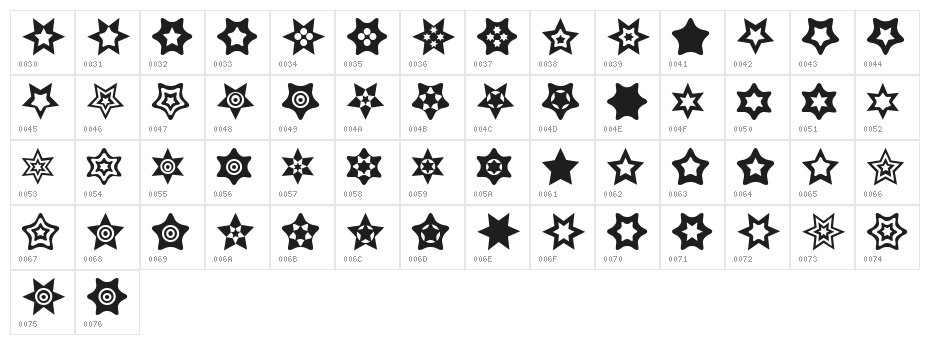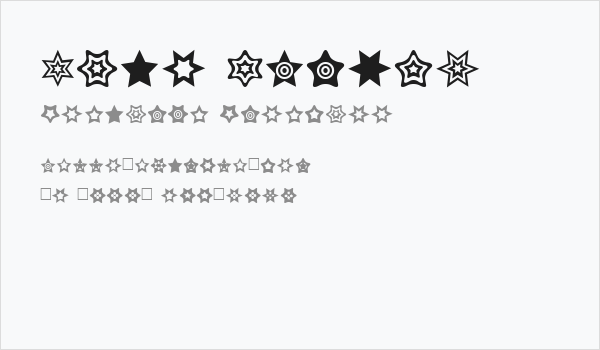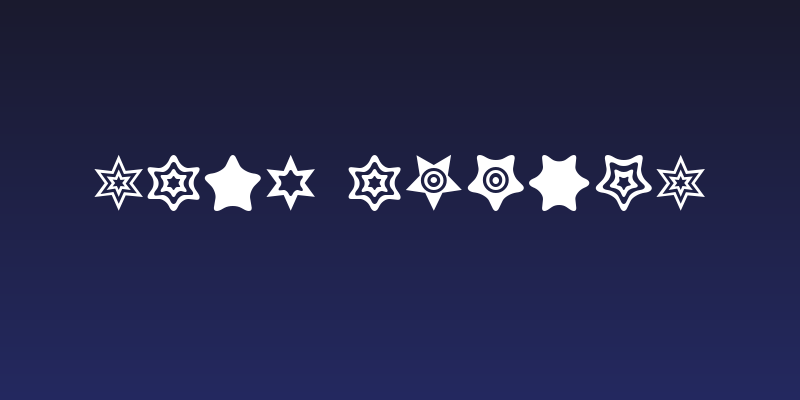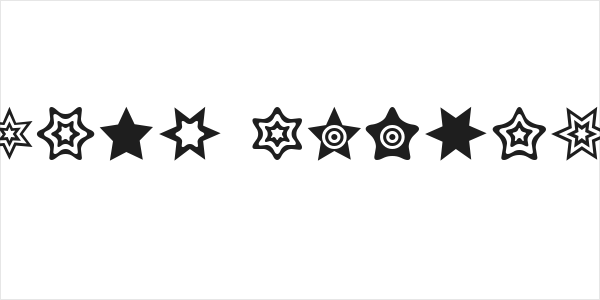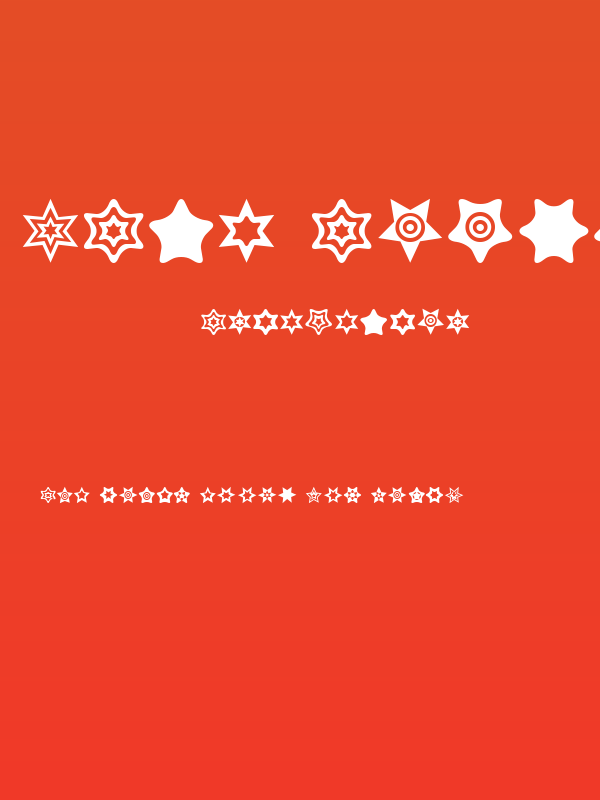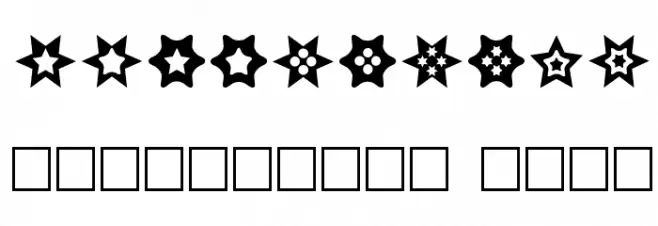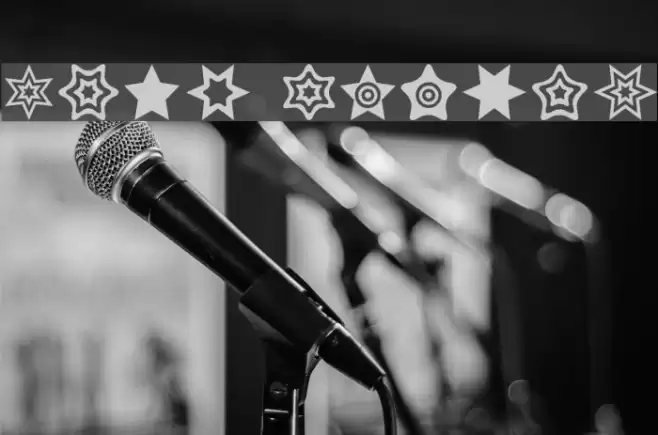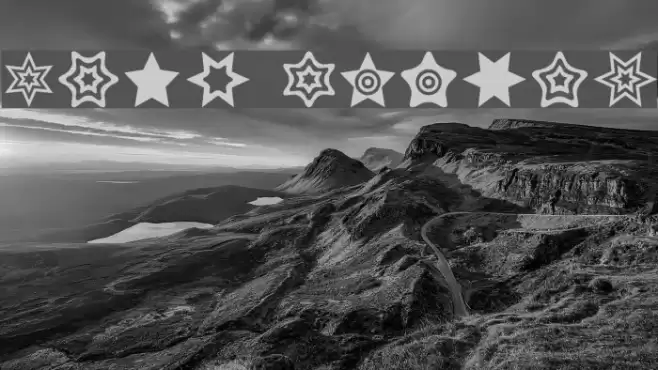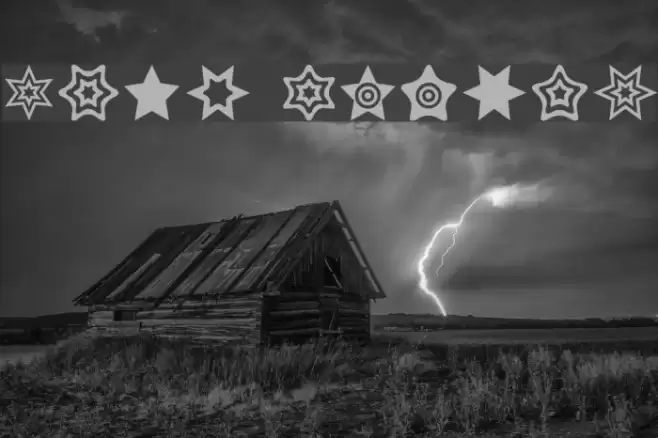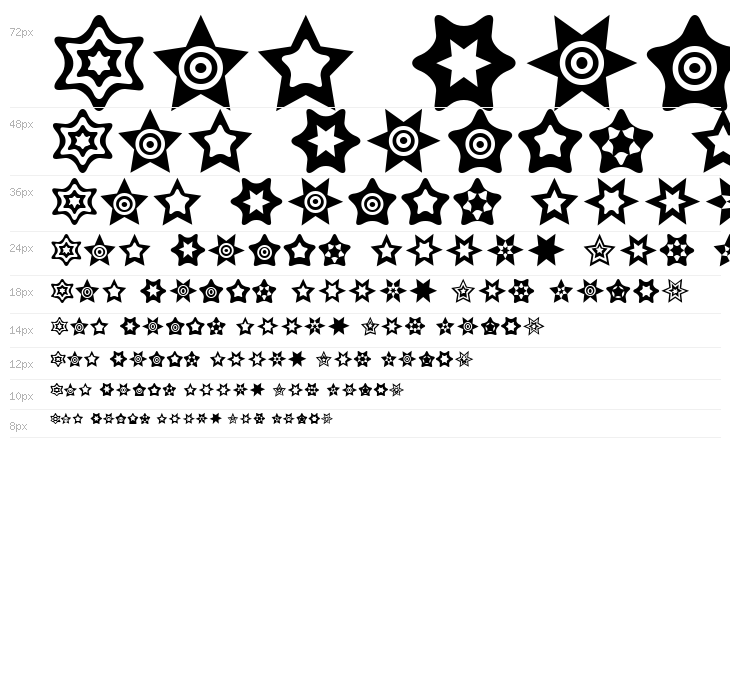
Star Things Font
| Caso d'uso | Decorative elements, Graphic design |
| Progetti proposti | These symbols could be used in graphic design projects, such as creating borders, embellishments, or decorative elements in invitations, posters, and digital artwork. |